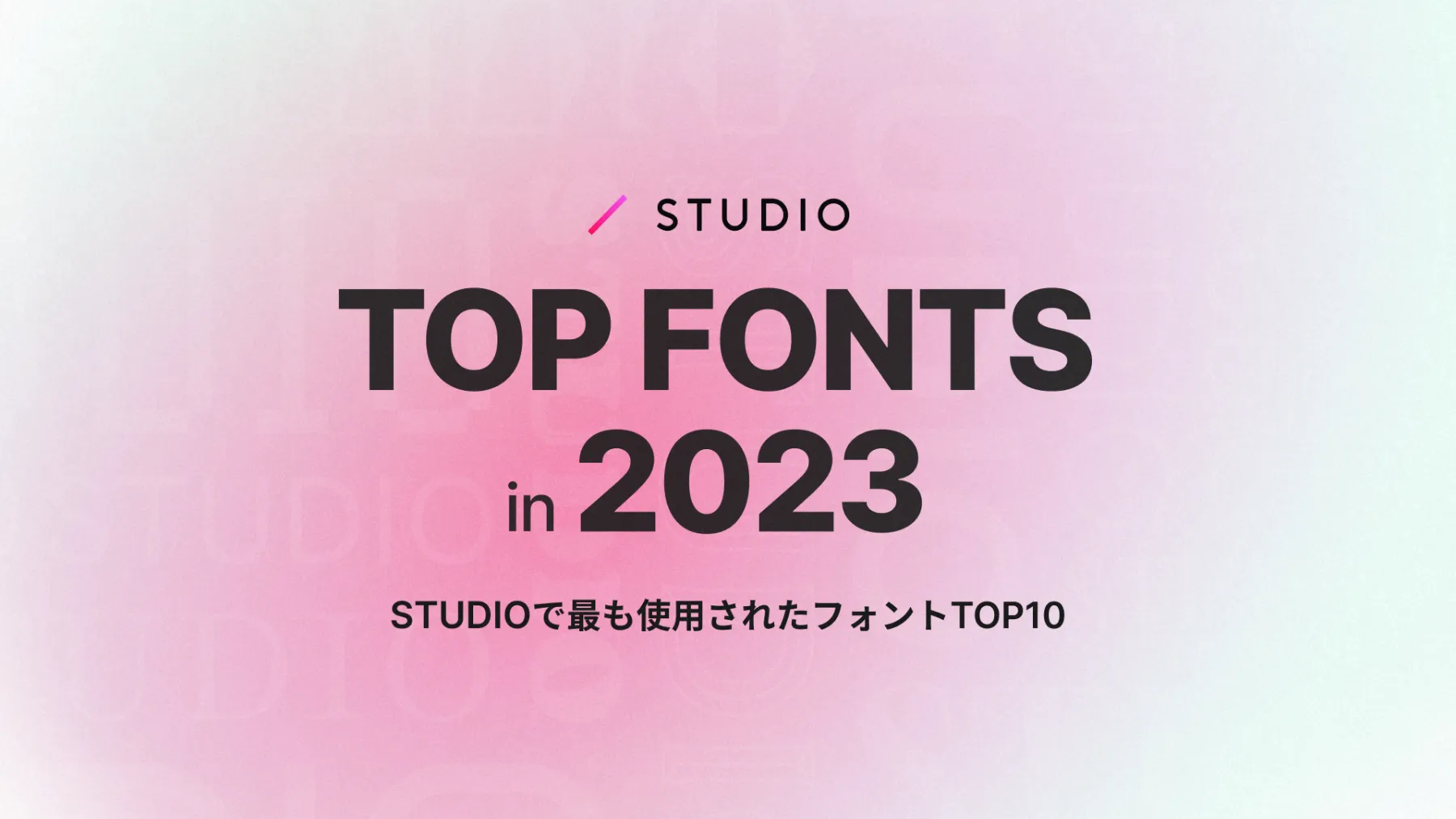
Studioフォントランキング2023!
Studioユーザーが使用したフォントランキング2023、Top10をご紹介します!
今年も残りわずかとなりましたね。 2023年には、STUDIOから多くのアップデートが行われました。8月には100以上の新しいフォントが追加され、STUDIOを利用したデザイン表現の幅が一層広がりました。 今年も去年に続き、STUDIOの一年を振り返る一環として「STUDIOフォントランキング2023」をご紹介します。 今回は、総合ランキングに加えて、Google FontsとTypeSquare別のランキングもご紹介しています。
去年のSTUDIO フォントランキング2022と比較しながら是非お楽しみください!
※初期フォントである「Lato」はランキングから除外しています。
1位 Noto Sans JP
1位:Noto Sans JP
サンセリフ体のフォントで日本語のひらがな、カタカナ、漢字に対応しています。フォントウェイトは6種類です。
2位 Roboto
親しみやすくオープンな曲線が特徴のフォントです。文字が自然な幅に収まり、より自然な読みのリズムを実現しています。
3位 Noto Serif JP
読みやすい明朝体のフォントで日本語のひらがな、カタカナ、漢字に対応しています。フォントウェイトは7種類です。
4位 リュウミン
金属活字に由来する彫刻刀の冴えを、左右のハライや点の形に活かしながらも、縦画・横画の先端やウロコにはやわらかさをもたせており、親しみやすい雰囲気になっています。
5位 A1ゴシック
"A1明朝の基本となる骨格を参照して作成された、オールドスタイルのゴシック体ファミリーです。線画の交差部分の墨だまり表現や、エレメントの端々に僅かな角丸処理を加えることで、温もりのあるデザインに仕上げています。"
6位 Montserrat
6位:Montserrat
クリーンでモダンな印象のサンセリフ体のフォントです。ブエノスアイレスの伝統的なモンセラット地区にある古いポスターや看板からデザインされました。
7位 ヒラギノ角ゴ
"「ヒラギノ角ゴ」は「ヒラギノ明朝」との組合せを意識してデザインされた角ゴシック体です。「ヒラギノ角ゴ」は、やや大きめの字面に対し、フトコロを少し締めることで、現代的な明るさを残しつつもオーソドックスな印象を与える書体です。"
8位 Inter
スクリーン上で表示するためにデザインされたフォントです。大文字と小文字が混在するテキストの可読性が高い特徴があります。
9位 Open Sans
Open Sansは、ニュートラルでありながら親しみやすい外観を持つようにデザインされているサンセリフ体のフォントです。ウェブ、モバイルにも最適化されています。
10位 Domine
10位:Domine
ウェブ上の本文用にデザインされ最適化されたフォントです。Clarendon、Century、Cheltenham、Clearfaceなど、100年以上前から使われている書体のクラシックな要素を組み合わせているため、見た目も親しみやすいです。
Google Fonts ランキング
順位
フォント
プロジェクト数
1位
Noto Sans JP
29630
2位
Roboto
24356
3位
Noto Serif JP
14466
4位
Montserrat
9279
5位
Inter
7527
6位
Open Sans
7439
7位
Domine
7335
8位
Rubik
5612
9位
Shippori Mincho
3445
10位
Poppins
3041
TypeSquare ランキング
順位
フォント
プロジェクト数
1位
リュウミン
11854
2位
A1ゴシック
10893
3位
ヒラギノ角ゴ
9139
4位
ゴシックMB101
5326
5位
A1明朝
3522
6位
中ゴシックBBB
1557
7位
こぶりなゴシック
1457
8位
Avenir
1352
9位
光朝
1012
10位
Source Sans Pro
743
最後に
いかがだったでしょうか? 今年は、去年1位だったA1ゴシックが今年は5位になり、Noto Sans JPが堂々の1位に躍り出ました。また、去年はランクインしていなかったリュウミンが4位にランクインするなど、興味深い結果になっています。 実際に公開されたSTUDIOサイトで使用されたフォントから、2023年の傾向が見えてくるかもしれませんね!